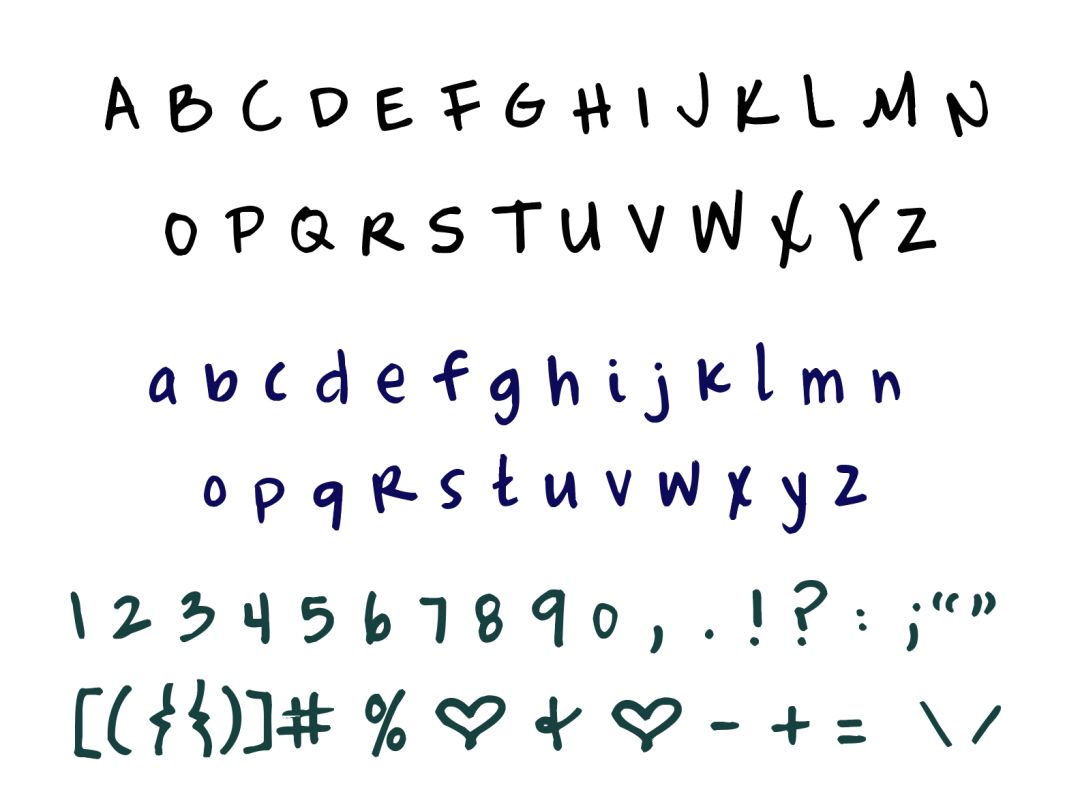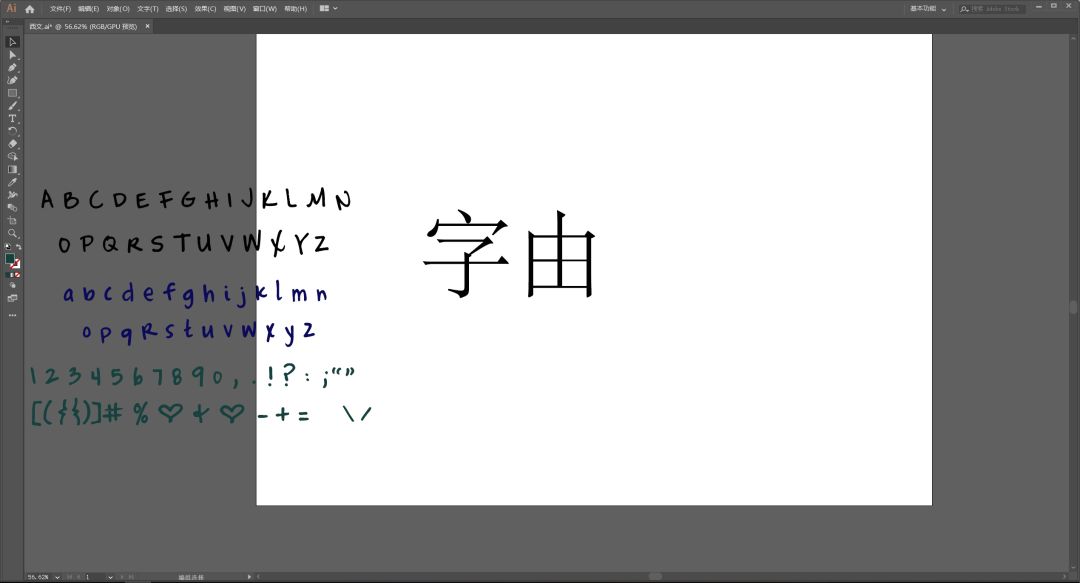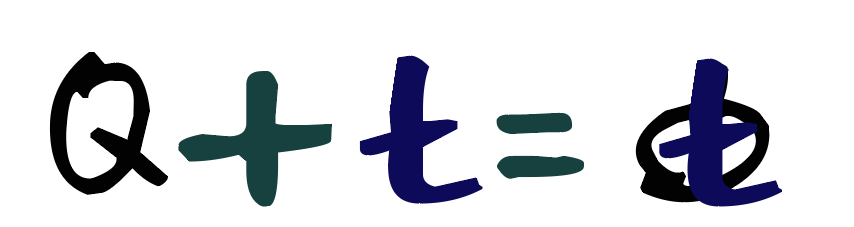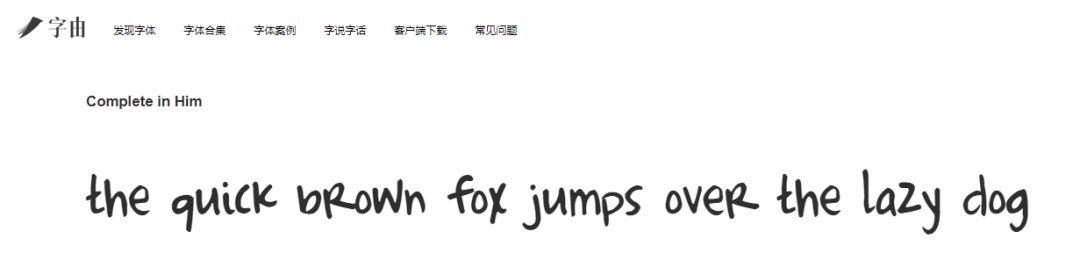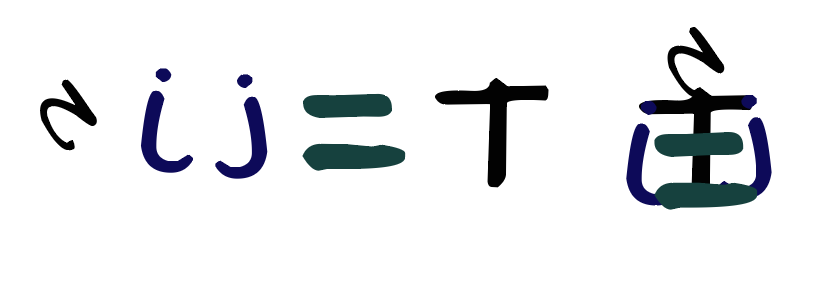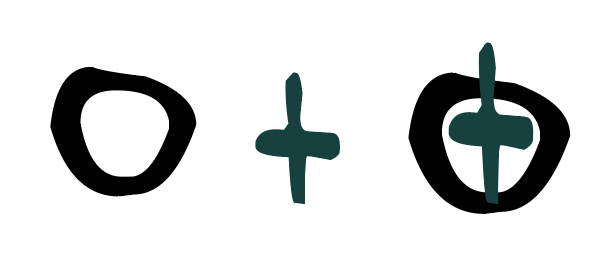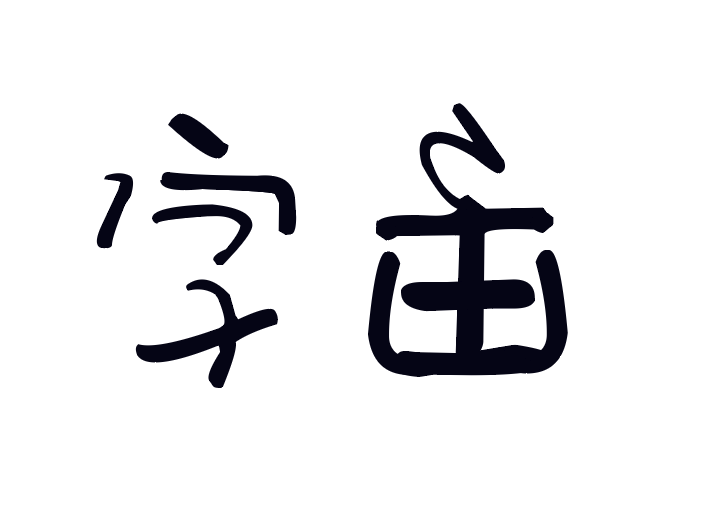
不想字体侵权的方法,你需要一套西文拼字大法
还记得之前柚子在看新闻要带脑子,做设计要带版权里说的,不想字体侵权,可以自己写,自己勾吗?
然后就有人说了,不是每个人都是潘老师,写得一手好字!
这点柚子可以亲测,我的字有时候本尊都不敢认,狂草派一枚,哪天晒出来给你们看看~
不过也不是不会写字,就没办法了,还有我们的好基友西文。有时候我还挺羡慕它们的,只需要26个字母,加上阿拉伯数字,就能出一套字体,效率远远赶超汉字的9169……
再加上它视觉呈现之丰富,完全可以被我们拿来西文中用,所以今天是一个很大胆地造字实验,跟我来吧~
在开始之前,先把西文的大、小写,数字标点都打出来。
然后上字由,选择一款手写感的字体。我对比了几个,最后定了Complete in Him~
框选所有字母,右键创建轮廓,并取消编组,现在可以来拼字了。
这时候你就不要把它当字母看待了,就把它当成一个元素,任何你觉得形似的笔画都列出来,比如这个:
然后继续发挥想象力,不要怕乱,因为柚子的画板上也是乱七八糟,不过风暴过后,发现“字”也可以这样拼。
从刚才的“电”发散开来,“由”字最简单的拼法就是~
不过我觉得没啥创意,又拼了一个破土而出的象形字。
略微调整,放在一起看看,虽然笔画间还有点不精致,但整体的形出来了~
今天主要是教你们一个拼字的思路,具体的还需要多多练习哦!